QuinScape Bestandteil des aktuellen Font Awesome Pakets
Font Awesome ist eine der beliebtesten kostenlosen Icon-Fonts auf dem freien Markt. In der aktuellen Version 4.0 ist das Logo der QuinScape fester Bestandteil.
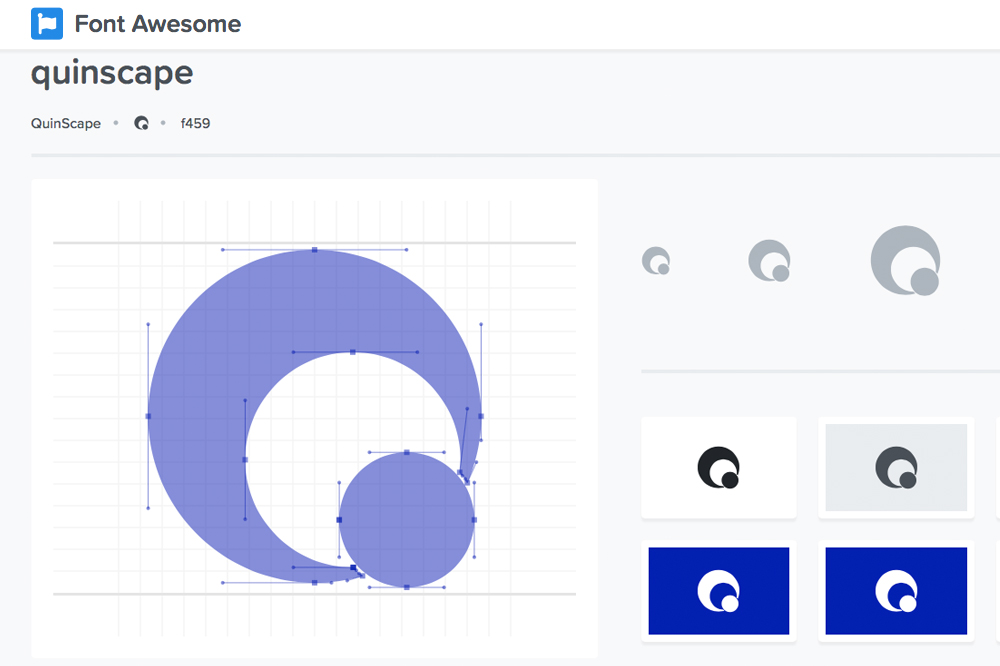
(firmenpresse) - Mit Font Awesome stehen mehr als 370 Icons für die Verwendung auf Webseiten zur Verfügung. Das Set hat gegenüber klassischen Icons den Vorteil, dass die Icons unendlich und verlustfrei skalierbar sind, mit CSS im Aussehen angepasst werden können und im Vergleich zu bildbasierten Lösungen deutlich weniger Kilobyte "auf die Waage" bringen. Anders als viele andere Icon-Fonts ist Font Awesome nicht nur gut anzusehen, sondern auch Screen-Reader-kompatibel.
Für das neue Release wurde der Icon-Font von Grund auf überarbeitet und für eine bessere Performance optimiert. Neben der Kompatibilität zu Bootstrap wurde auch eine bessere Kompatibilität mit anderen Frameworks – beispielsweise dem Foundation-Framework – hergestellt. Hierfür wurden u. a. die Namenskonventionen für den Einsatz der Icons komplett überarbeitet. Zentraler Vorteil: eine sehr einfache Handhabung, überall auf Welt einsetzbar und ein fester Bestandteil des fontawesome-free-5.0.6.
Im Schulterschluss mit den großen Brands wie Amazon, Facebook, Twitter, Angular, Bitcoin, firefox, flickr, Jenkins, joomla, lastfm, napster, xbox, yahoo wurde auch dass Font-Awesome-Logo von QuinScape in seiner aktuellen Version aufgenommen. Als innovativer Dienstleister für moderne IT-Lösungen unterstützt die QuinScape GmbH gerne entsprechende Projekte und aufgrund der Spezialexpertise für User Interfaces und User Experience ist es für den Dortmunder IT-Dienstleister auch generell nützlich, mit dem Logo vertreten zu sein.